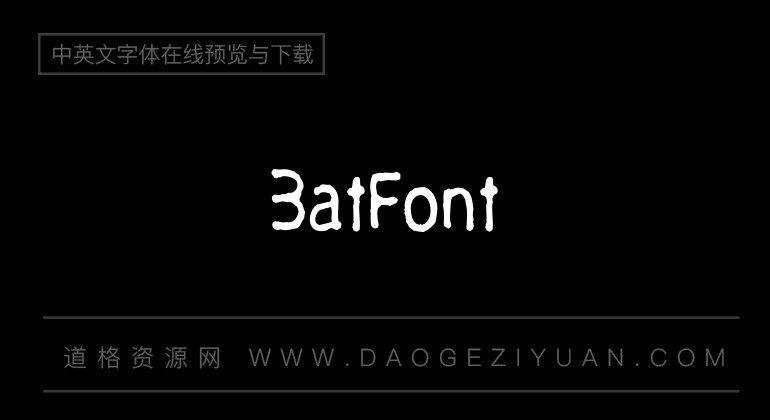
BatFont 是一款由美国设计师 Paul Antonio 创作的漫画风格字体,它采用了比较粗糙的线条,具有明显的节奏感,能够给文字添加一种活力的感觉。它的字体特点是比较大胆,有一定的视觉冲击力,可以用来突出重点,强调重要信息。此外,BatFont 还具有一定的玩味性,可以给文字增添活力,使用它可以让文字更加有趣。内容介绍
BatFont是一款非常不错的手写艺术字体,具有很好的视觉感,适合于文化类的宣传设计、商业类品牌的广告和产品包装设计以及个性化文字排版等较多场景。